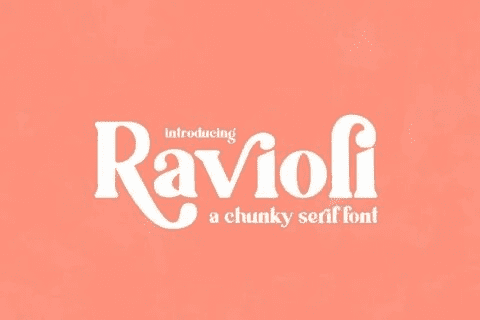
Название: Ravioli Font
Равиоли - это прохладный и лохматый шрифт с засечками.
Его легко подогнать под невероятно большой набор проектов, так что добавьте его к вашим творческим идеям и заметьте, как он выделяет их на фоне других!